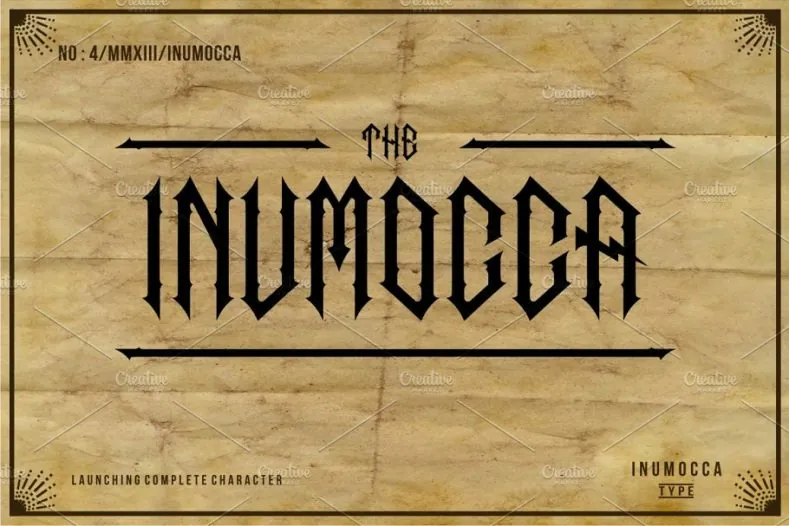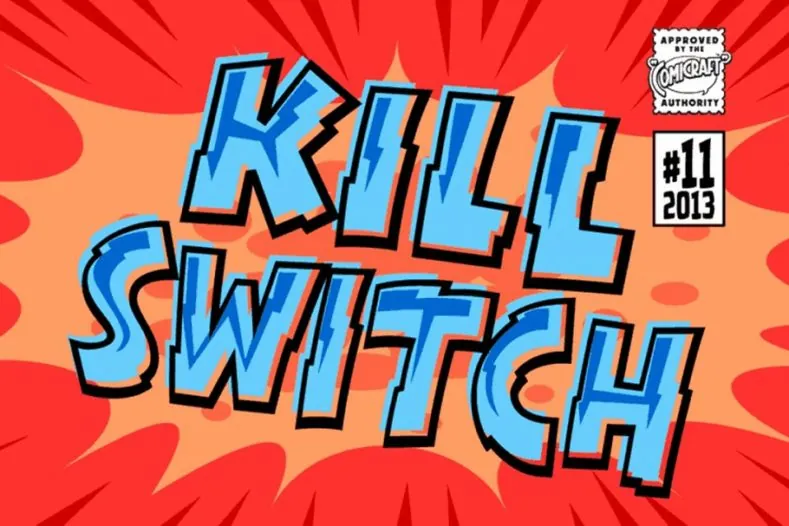
Colección de tipografías eléctricas para que te descargues gratis y premium. Una tipografía u otra puede cambiar el aspecto de un diseño, puede mejorarlo o empeorarlo. Por eso es muy importante utilizar la fuente adecuada para cada proyecto. Con las fuentes con efecto eléctrico tipo flash conseguirás que parezca que hay movimiento en tipografías completamente estáticas. Con algunas de ellas conseguirás provocar miedo o sorpresa. Que decir de la tan famosa tipografía rayo, descarga estas letras tan diferentes. Entreten a tu audiencia con estas letras eléctricas tan originales en tus trabajos. Aquí las tienes, escogidas para ti:
Fonts eléctricas premium
Más abajo podrás ver tipografías gratis, aquí te indico unas premium de gran calidad que te garantizan un buen trabajo de diseño con ellas. Están recomendadas para diseñadores gráficos profesionales.
Inumocca, una gran letra eléctrica
Killswitch, te servirá para comics
Nada más verla ya impacta, es una gran tipografía premium.
Tipografías eléctricas gratis
Electrical
Esta fuente de letra electrica no tiene los carácteres latinos, ni tildes ni ñ pero no se puede negar que es espectacular aunque no tenga los caracteres latinos.
In A Flash
Letra con rayos y con efecto flash.
Inner Flasher
Tipografia electrica similar a la anterior con ese efecto flash. Es una tipografia rayo, como en una tormenta.
Sound-Sample
Otra tipografia electricidad que simula el sonido de unos altavoces.
Zippo
Mad Science
En la imagen podrás ver una fuente de letra electrica.
Space Patrol
Otra tipografía rayo para que la guardes.
NADC Soundbeat
En este caso es una tipografia electronica, aunque también puede ser considerada electrica, ¿o no? Te servirá para diseños relacionados con la música electrónica.
Zacken
Lightning Strike
Ride the Lightning
Lightning Volt font
ShockTherapy BB
En shock entrarás al ver esta fuente, así que si quieres dar miedo o sorpresa anímate a utilizar esta tipografía.
Shock font
Electrickle font
KR Electrified font
Aarcover font
Furry font
Electric Hermes AOE font
Zeus font
Es ideal para música electrónica aunque si le encuentras un uso mejor, adelante.
Tipos de Tipografías Eléctricas Populares
Aquí tienes una lista de estilos de tipografías de electricidad que puedes explorar para tus proyectos:
- Tipografía de Rayos Realistas
- Fuentes como Thunderstorm o Lightning Bolt destacan por su apariencia realista de rayos.
- ¿Dónde usarla? Diseños relacionados con eventos de música, videojuegos o deportes.
- Pro tip: Estas letras con rayos son ideales para combinarlas con fondos oscuros o efectos de neón.
- Tipografía Electrificada Minimalista
- Para un diseño más limpio, fuentes como Electric Dreams o Neon Lightning ofrecen un enfoque moderno y estilizado.
- ¿Dónde usarla? En logotipos tecnológicos, carteles de ciencia ficción o diseños futuristas.
- Electricidad en Cursiva
- Si buscas electricidad en letra cursiva, puedes probar fuentes como Zapfino Electric o Script Lightning. Estas opciones combinan elegancia con un toque electrizante.
- ¿Dónde usarla? Invitaciones temáticas, diseño editorial o marcas de lujo con un toque moderno.
Consejos para Usar Tipografías de Electricidad en tus Diseños
- Resalta con colores brillantes: Las tipografías eléctricas lucen mejor en tonos como amarillo, azul neón o blanco brillante, combinados con fondos oscuros o degradados.
- Añade efectos luminosos: Para potenciar el efecto de las letras tipo rayo, utiliza programas como Photoshop o Illustrator para aplicar filtros de brillo, sombras suaves o destellos.
- Úsalas con moderación: Estas fuentes son llamativas, así que es mejor usarlas en títulos, encabezados o elementos destacados, evitando saturar el diseño.
Crea Proyectos que Impacten con Letras Electrificantes
Ya sea que necesites letras eléctricas para un logotipo, un cartel promocional o simplemente para experimentar con un estilo diferente, estas fuentes son ideales para captar la atención de tu audiencia. Desde letras con rayos hasta diseños que simulan electricidad en cursiva, las posibilidades son infinitas.